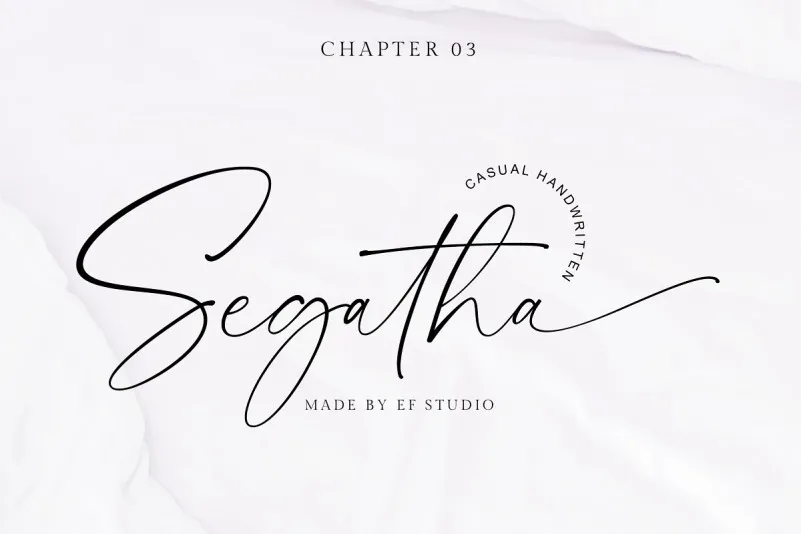
Segatha Handwritten Font – Download Grátis
Aproveite para baixar a Segatha Handwritten Font, uma elegante escolha entre as fuentes script. Esta é uma fonte casual que transmite personalidade e curvas suaves, perfeita para quem procura um touch a mais de criatividade em seus trabalhos digitais. O designer f0rdesigner utilizou pequenos traços rápidos para criar este font naturalmente, oferecendo uma aparência autêntica mesmo em plataformas online. Segatha Handwritten é perfeito tanto para criação de marca, convites, marcas d’água e fotografia como para qualquer projeto que deseje dar um toque único e atraente. Com suas letras maiúsculas e minúsculas que começam e terminam em curvas suaves, bem como 94 ligações adicionais que criam mais opções estéticas, o Segatha Handwritten ajuda você a finalizar projetos de um modo extraordinário. Esta fonte é perfeitamente adequada para diversos usos, garantindo que sua marca se destaque entre as demais. Essa fonte será uma ótima adição à sua biblioteca de recursos gráficos, deixando seu trabalho mais personalizado e inovador. Seja em um projeto digital ou impresso, a Segatha Handwritten vai ajudá-lo a capturar a essência da sua ideia com estilo e elegância.